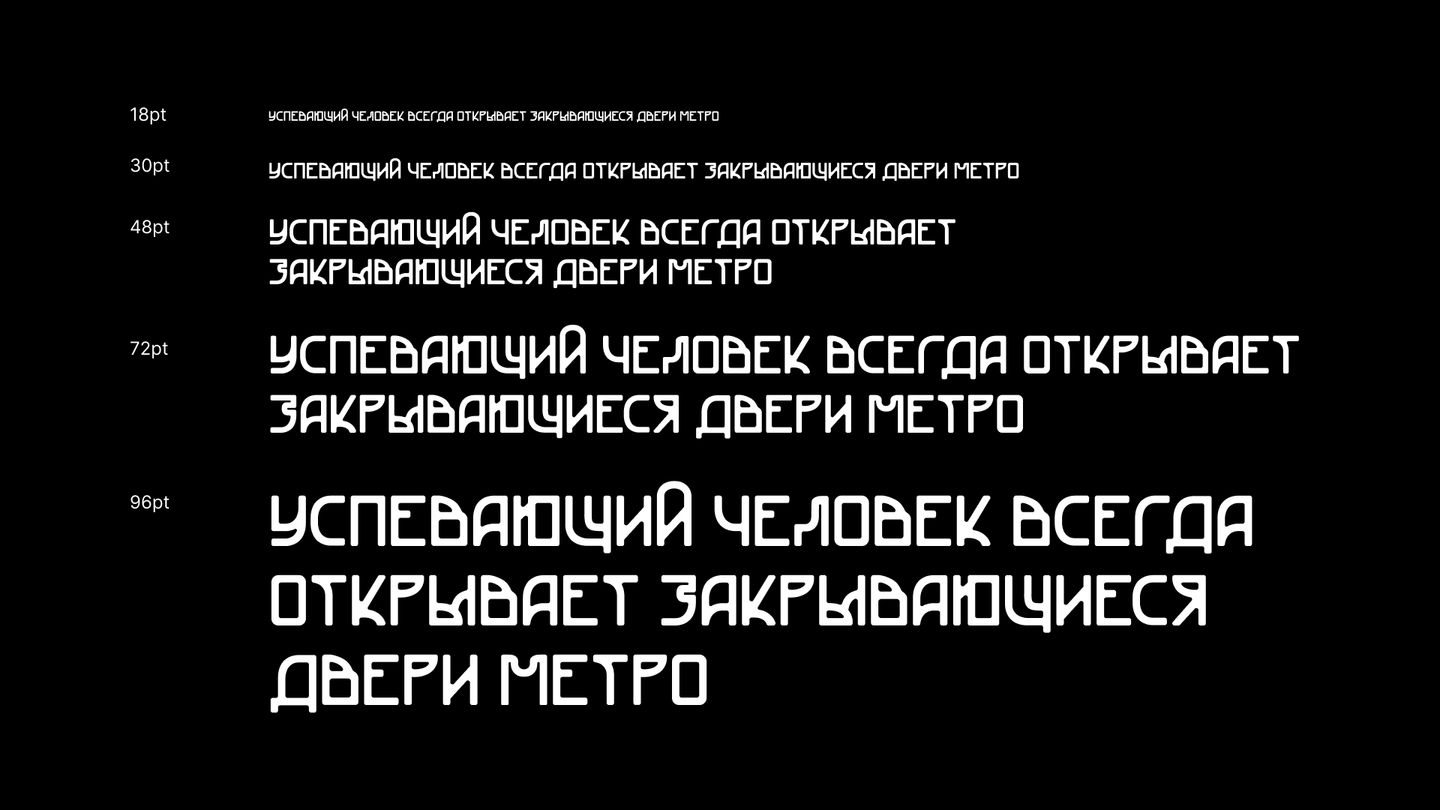
Акцидентный шрифт Izgib вдохновлен поручнями метрополитена и общественного транспорта. Каждая буква повторяет очертания поручней, их соединительные швы, округлые формы и цельную конструкцию.
Особенности
Кириллица
Латиница
Цифры и знаки